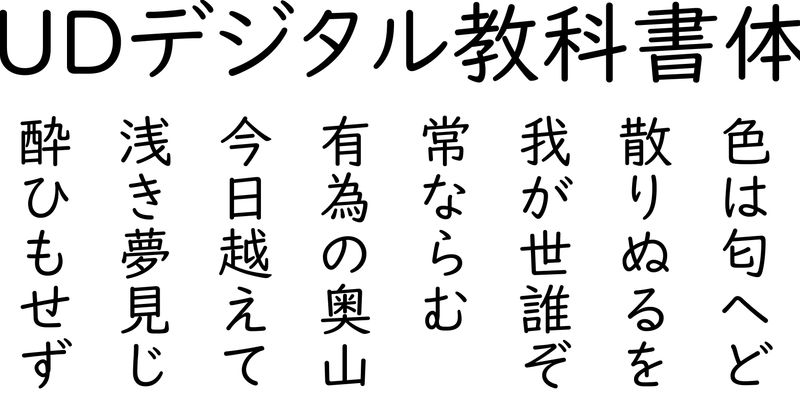
UD Digital Kyokasho ist eine universelle Design-Schrift für ICT-basierte Lehrmaterialien, wie z. B. digitale Lehrbücher. Sie ahmt die Handschrift mit einem Bleistift oder Filzstift nach, wobei der Schwerpunkt auf der Bewegung der Hand liegt. Die Achsenrichtung, die Form der Punkte und das Harai-Ende wurden beibehalten, aber die Striche sind weniger kontrastreich, um für Menschen mit Sehschwäche und Legasthenie geeignet zu sein. Die Struktur ist näher an der Schreibschrift für Schulbücher als an den konventionellen, auf den nationalen Richtlinien basierenden Buchstabenformen für den Unterricht.